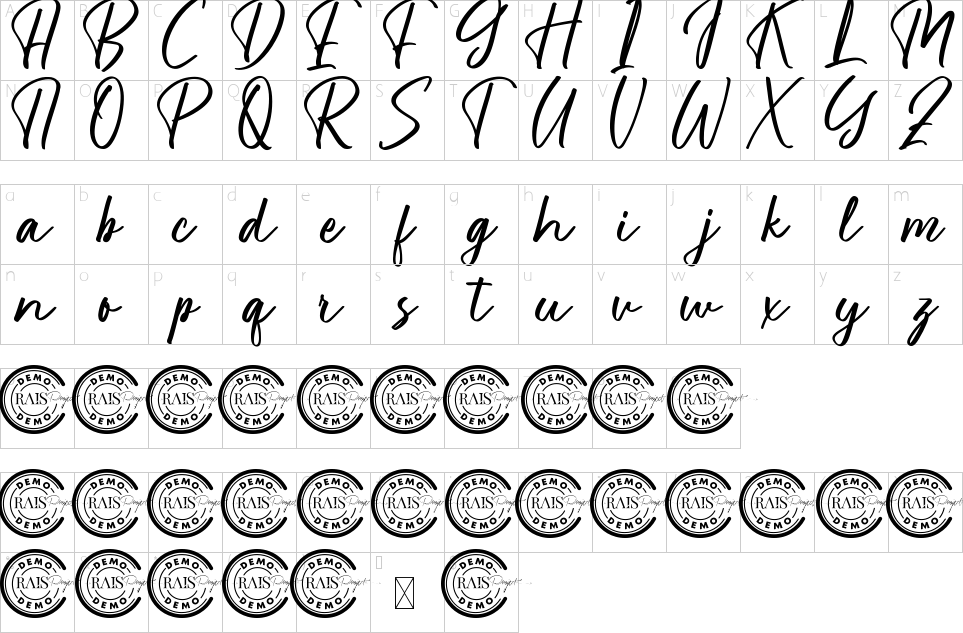
Descubra a alegria da natureza em cada letra com a Fonte Passafluente. Desenvolvida pelo RaisProject, a fonte Passafluente transmite uma energia vibrante e inspiradora que vai refletir sua identidade de escrita e criar um ambiente único para seu projeto. Com seus traços delicados e uma paleta de cores incríveis, essa fonte é perfeita para qualquer aplicação de design gráfico que deseje trazer à vida. Com uma elegante tipografia que remete à natureza, essa fonte é um toque de criatividade que vai dar um novo olhar a seus designs. Descubra por que mais de 2,330 pessoas já aderiram à Passafluente. Que tal adicionar um toque de natureza e inspiração a seu próximo projeto? Descubra a Passafluente agora.